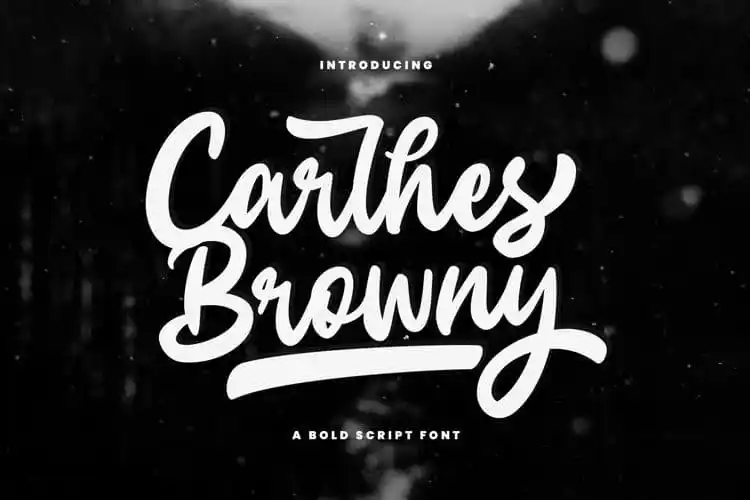
Carlhes Browny Bold Script Font – Fonte Grátis
Carlhes Browny Bold Script Font
A Carlhes Browny Bold Script Font é uma elegante tipografia script bold, projetada para aqueles que buscam personalidade e estilo moderno em seus trabalhos de design. Com aparência deslumbrante, esta fonte tem tudo o que você precisa para reforçar sua identidade visual. É perfeitamente adaptável a logotipos, cabeçalhos de sites, criação de moda, anúncios e muito mais. O designer, sizimon, criou este tipo de letra com um forte impacto visual, tornando-a ideal para qualquer projeto que deseje destacar-se. Seu estilo sofisticado e elegante a torna uma excelente opção para qualquer trabalho em design onde se espera um toque especial, seja na construção de uma marca ou no desenvolvimento de uma página web. A fonte contém todo o conjunto necessário de letras maiúsculas e minúsculas, um amplo leque de sinais de pontuação, numerais e suporte multilíngue. Com a Carlhes Browny Bold Script Font, você pode adicionar um toque único e inovador ao seu trabalho de design. Seja para uma identidade visual robusta, um site atraente ou mesmo um projeto em desenvolvimento de moda – esta fonte oferece tudo que precisa para dar o tom certo à sua criação.